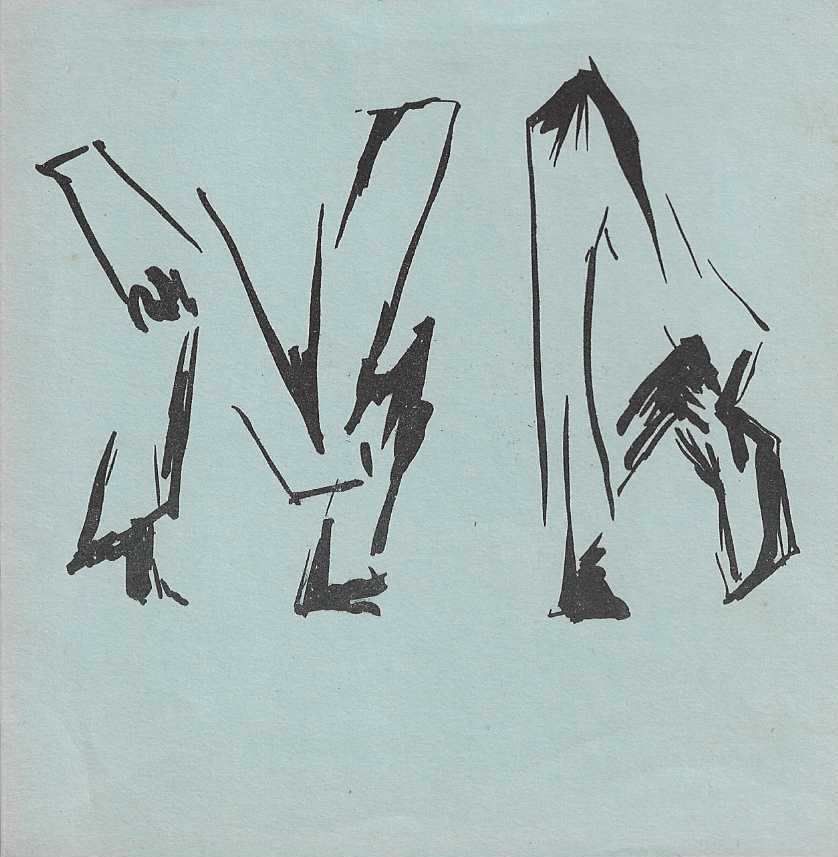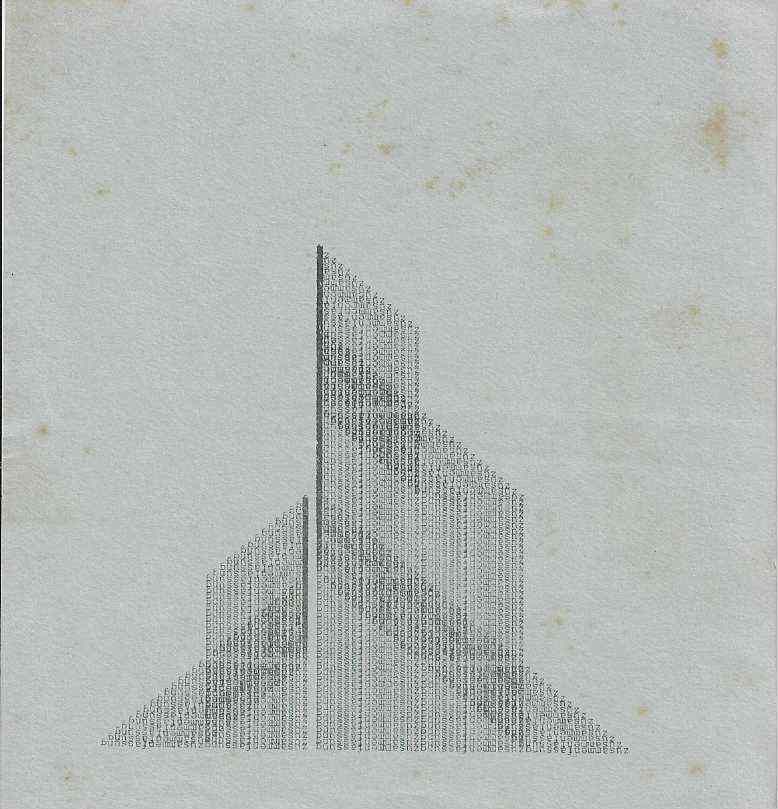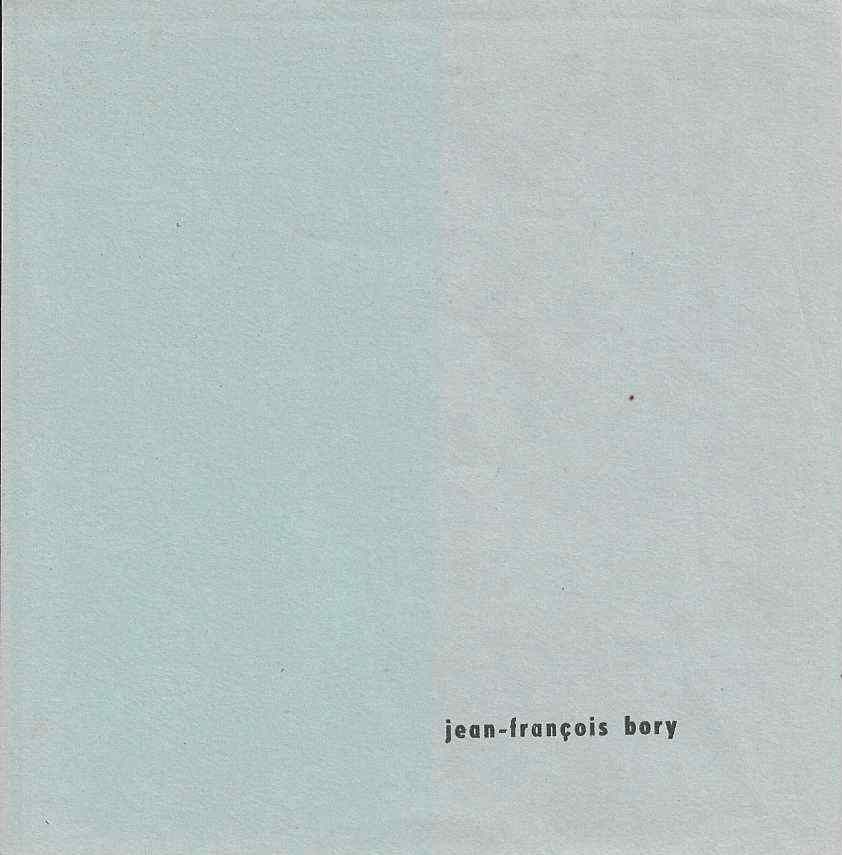
Conjunto de três impressões gráficas sobre papel do artista francês Jean François Bory, relacionado à sua investigação sobre poesia visual, poesia concreta, escrita, tipografia e transformação da linguagem verbal em estrutura gráfica.
Jean François Bory - França
Conjunto de três impressões gráficas sobre papel do artista francês Jean François Bory, relacionado à sua investigação sobre poesia visual, poesia concreta, escrita, tipografia e transformação da linguagem verbal em estrutura gráfica. As três peças apresentam procedimentos distintos, mas complementares, demonstrando como Bory utiliza desenho, impressão, letras, números e organização espacial como componentes de uma linguagem poética que ultrapassa a leitura convencional.
A primeira impressão apresenta uma composição gestual em preto sobre papel de tonalidade azul clara. Grandes formas verticais e diagonais ocupam a parte superior e central da folha e sugerem simultaneamente letras, sinais gráficos, corpos ou estruturas em movimento. A imagem preserva características do desenho manual, com variações de espessura, interrupções, sobreposições e marcas expressivas. O resultado situa a obra entre escrita e desenho, tornando incerta a separação entre signo linguístico e forma visual.
A segunda impressão apresenta uma construção geométrica formada por uma grande quantidade de pequenos caracteres tipográficos organizados em linhas verticais e diagonais. Os sinais se acumulam até formar uma estrutura semelhante a uma arquitetura, montanha ou volume tridimensional. O poema deixa de depender da leitura sucessiva das unidades impressas e passa a funcionar por densidade, repetição, ritmo, direção e concentração gráfica.
Esse procedimento está diretamente relacionado às pesquisas desenvolvidas por Jean François Bory desde a década de 1960 em torno da máquina de escrever, da poesia concreta e da mecanização da escrita. Letras, números e sinais deixam de servir exclusivamente à formação de palavras e passam a constituir matéria para construção de imagens. A página funciona simultaneamente como superfície de leitura e espaço plástico.
A terceira folha apresenta composição extremamente reduzida. Grande parte do papel permanece vazia e apenas o nome jean françois bory aparece impresso próximo à região inferior. O amplo espaço em branco transforma a ausência de texto e imagem em elemento ativo da composição. A assinatura tipográfica funciona simultaneamente como identificação do autor, presença textual e unidade gráfica.
Consideradas em conjunto, as três impressões demonstram diferentes possibilidades de transformação da escrita em imagem. A primeira explora o gesto e a ambiguidade entre desenho e letra. A segunda trabalha a acumulação mecânica e estrutural de caracteres tipográficos. A terceira utiliza redução, silêncio visual e vazio. Essas estratégias são características da pesquisa de Jean François Bory sobre os limites entre poesia, linguagem, tipografia, página e artes visuais.
Não há data, título individual, tiragem ou técnica editorial identificáveis com segurança nas imagens apresentadas. Essas informações devem permanecer em aberto até que sejam localizados colofão, verso, assinatura, catálogo ou outra documentação associada ao conjunto.
Set of three graphic prints on paper by French artist Jean François Bory, related to his investigation of visual poetry, concrete poetry, writing, typography and the transformation of verbal language into graphic structure. The three works employ different but complementary procedures, demonstrating how Bory uses drawing, printing, letters, numbers and spatial organization as components of a poetic language that moves beyond conventional reading.
The first print presents a gestural composition in black on light blue paper. Large vertical and diagonal forms occupy the upper and central areas of the sheet and simultaneously suggest letters, graphic signs, bodies or structures in movement. The image preserves the characteristics of manual drawing through variations in thickness, interruptions, overlapping marks and expressive gestures. The result places the work between writing and drawing, making the distinction between linguistic sign and visual form deliberately uncertain.
The second print presents a geometric construction formed by a large quantity of small typographic characters arranged in vertical and diagonal lines. The signs accumulate to create a structure resembling architecture, a mountain or a three dimensional volume. The poem no longer depends on the sequential reading of the printed units and instead operates through density, repetition, rhythm, direction and graphic concentration.
This procedure is directly related to Jean François Bory's investigations since the 1960s into the typewriter, concrete poetry and the mechanization of writing. Letters, numbers and signs cease to function exclusively as elements for constructing words and become material for constructing images. The page operates simultaneously as a reading surface and a visual field.
Set of three graphic prints on paper by French artist Jean François Bory, related to his investigation of visual poetry, concrete poetry, writing, typography and the transformation of verbal language into graphic structure.